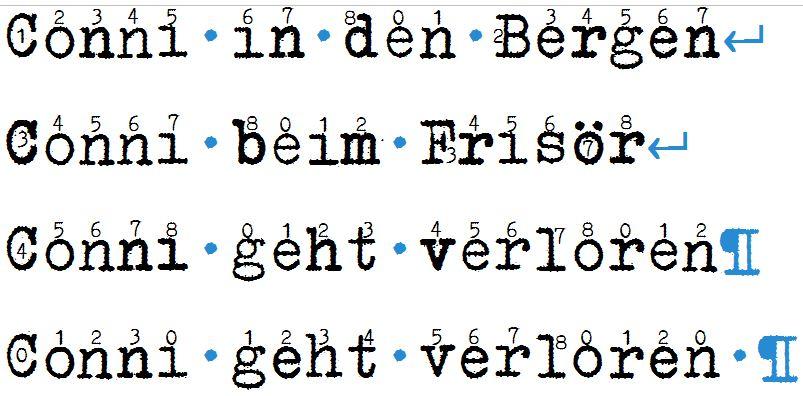
Ich suche eine schöne Schreibmaschinenschrift
Ja, das ist richtig, und gefällt mir eigentlich auch nicht, aber ich kenne da leider keinen Weg, das zu umgehen.
Die Sache läuft ja eigentlich nicht über einen Zähler, sondern nach dem Motte: Der Buchstabe davor entscheidet.
So schlimm finde ich das gar nicht, Mir fiel das nur auf, weil ich im Test mehrfach die gleichen Buchstaben pro Zeile ausgebe. Aber in der Praxis ist das ja wohl ein eher seltenes Phänomen und betrifft höchstens den Fall, das der erste Buchstabe zweier Zeilen der gleiche ist. Das wird man kaum merken, denke ich – wir schauen ja grad auch alle besonders genau hin ;-)
Na ja, bei meiner Testseite hatte ich in drei recht dicht folgenden Zeilen das gleiche Wort, und das kommt dann natürlich komplett einheitlich. In so fern hätte ich schon gern eine Lösung.
Aber nur, wenn die durch 9 geteilte Zeilenposition (ohne Leerzeichen) des Wortanfangs immer denselben Rest ergibt, oder? http://type.dt1.org/font/cat/erikas-farbband/#rotation
Allerdings könnte der Effekt vielleicht sichtbar werden, wenn man wirklich Texte hat, in denen mehrere aufeinander folgende Zeilen mit denselben Zeichenketten beginnen, etwa so: http://type.dt1.org/font/cat/erikas-farbband/#conni
Ließe sich der Effekt, ohne den Rotationseffekt an sich zu verkomplizieren, vielleicht vermeiden, indem man Nutzern erlaubt, per cv0X(Zeichen) einfach den x-te Variante eines Zeichens manuell auszuwählen? Würde es dann im nächsten Zeichen automatisch mit der x+1. Variante weitergehen?
Leider klappt das alles nicht. Auch die Handeingabe, denn was sollte der Nutzer da eingeben, und zum 2. kann ich ja keine Variablen verwenden, OpenType ist nun einmal keine Programmiersprache.  Also gut, geht nicht anders.
Das neueste Fundstück von TobiW und die durchweg positive Reaktion auf ErikaFarbband haben mich darüber nachdenken lassen, was dann an echten Bleisatz Akzidenzen so toll ist, wie sie Martin so herstellt.
Es ist sicher nicht die sicher tolle handwerkliche Satzqualität, denn das dürften nach mehreren Jahren der Entwicklung auch typopgrafisch geschulte Anwender an guten Satzprogrammen hin bekommen. Es ist sicher auch nicht diese Fühlbarkeit nach Letterpress-Manier, denn die ist handwerklich eigentlich nicht wirklich so OK.
Ich glaube, es sind die winzigen, kaum sichbaren Zufälligkeien durch abgenudelte oder im Setzkasten angestoßener Lettern, etwas Druckfarbe, die sich über die Konturen quetscht - alles kaum sichtbar, aber eben doch anders als immeer 100% identische Computerbuchstaben. In der Natur ist nichts 100% symmetrisch und Glatt.
Und dies hat mich jetzt dazu gebracht, noch einmal eine nur noch dezent unakkurate Version zu bauen, die ich ErikasBüro genannt habe, damit beide nebeneinander installiert werden können. in Fontforge genau nach Fehlern durchsucht, da ist diese Software ja wirklich super pingelig, echt Klasse, auch wenn ich das UI gar nicht mag.
Die sache mit codierten Subscript und Superscript- Ziffern liegt noch in der ToDo-Liste
Ich glaube, es sind die winzigen, kaum sichbaren Zufälligkeien durch abgenudelte oder im Setzkasten angestoßener Lettern, etwas Druckfarbe, die sich über die Konturen quetscht - alles kaum sichtbar, aber eben doch anders als immeer 100% identische Computerbuchstaben. In der Natur ist nichts 100% symmetrisch und Glatt.
1. Worauf willst du hinaus? Darauf, dass mit Bleilettern gedruckter Text wegen der Unregelmäßigkeiten besser lesbar ist? Oder wegen der Unregelmäßigkeiten irgendwie angenehmer ist? Ich finde Erikas Farbband wirklich schön, um am Bildschirm einen Schreibmaschineneffekt zu erzielen, aber ich bezweifele, dass sie wegen der Unregelmäßigkeiten angenehmer zu lesen ist als eine Erika-Version, die auf Basis von Zeichen entstanden ist, die unter Idealbedingungen getippt wurden, unter denen es zu keinen Unregelmäßigkeiten kommt. Solche Idealbedingungen gibt es bei der Erika nicht, selbst wenn Maschine und Farbband fabrikneu und handverlesen sind. Worauf ich hinaus will, ist, dass sich die getippten Zeichen auch unter solchen Idealbedingungen von den Zeichnungen der Zeichen, die Basis für die Typen der Maschine waren, unterscheiden werden. Und da sind wir ganz schnell beim Thema Optical Sizes.
2. Mir fällt bei manchen Antiquas auf, dass sie beim Lesen zu einer Art Linienbildung neigen, u. z. nicht auf Höhe der Serifen. Ich konnte mir das bisher nur durch eine zu große Regelmäßigkeit erklären, z. B. (!) damit, dass sich der Winkel der Achsen in den Zeichen, die die Punkte der schmalsten Stellen im Kurvenverlauf schneiden, zwischen den Zeichen nicht deutlich genug oder gar nicht unterscheiden. Die Stempel Garamond empfinde ich z. B. als wunderbar rhythmisch. Ich kann den unangenehmen Effekt der Linienbildung nicht besser beschreiben, aber die Stempel Garamond neigt überhaupt nicht dazu. Die Wortbilder sind ein perfektes Zusammenspiel aus Symmetrie und Asymmetrie.
3. Es gibt in der unbelebten Natur schon recht viele Formen, die höchst symmetrisch sind oder zumindest so auf den Menschen wirken, z. B. die Formen von Kristallen. Ich glaube aber auch, dass wir Menschen perfekte Symmetrien nicht als lebendig empfinden. Sie können irritieren.
vor 1 Minute schrieb Arno Enslin:
Darauf, dass mit Bleilettern gedruckter Text wegen der Unregelmäßigkeiten besser lesbar ist? Oder wegen der Unregelmäßigkeiten irgendwie angenehmer ist?
Nein, nicht dass diese Unregelmäßigkeiten irgendwie das Lesen erleichtern, nein, ganz und gar nicht. Drum habe ich ja auch von typischen Akzidenzen gesprochen, bei denen der Text eben nicht nur die bloße Informationsübermittlung sein soll, sondern auch ein wenig Gefühl mitschwingt. Und so wirkt dann der Handsatz-Text auf der Visitenkarte trotz dessen dass er in einer sauberen Satzschrift gesetzt ist, und das nach allen Regeln der Kunst durch diese kaum sichtbaren leichten Unregelmäßigkeiten irgedwie organischer, ohne das es direkt jemand sagen würde.
Ich muss nur die Features, die etwas wie »sub z by« machen nur VOR der Zirkelei setzen
Was den FF-Bug anbelangt, das hatte ich mir schon gedacht. Diesen Versuch-Font hatte ich mir ja zum Test der OpenType-Spieleri in LibreOffice gebaut.
Übrigens geht dieser Eingriff erst nach dem 2. Buchstaben und nur im ersten Wort. Hat das erste Wort nur 2 Buchstaben, gibt es keine Eingriffsmöglichkeit. Im Rest der Zeile ist der Bindehemmer eben der Bindehemmer, mehr nicht.
Als ich gerade an Erikas Farbband und das Rotationsfeature dachte, fiel mir das hier ein: